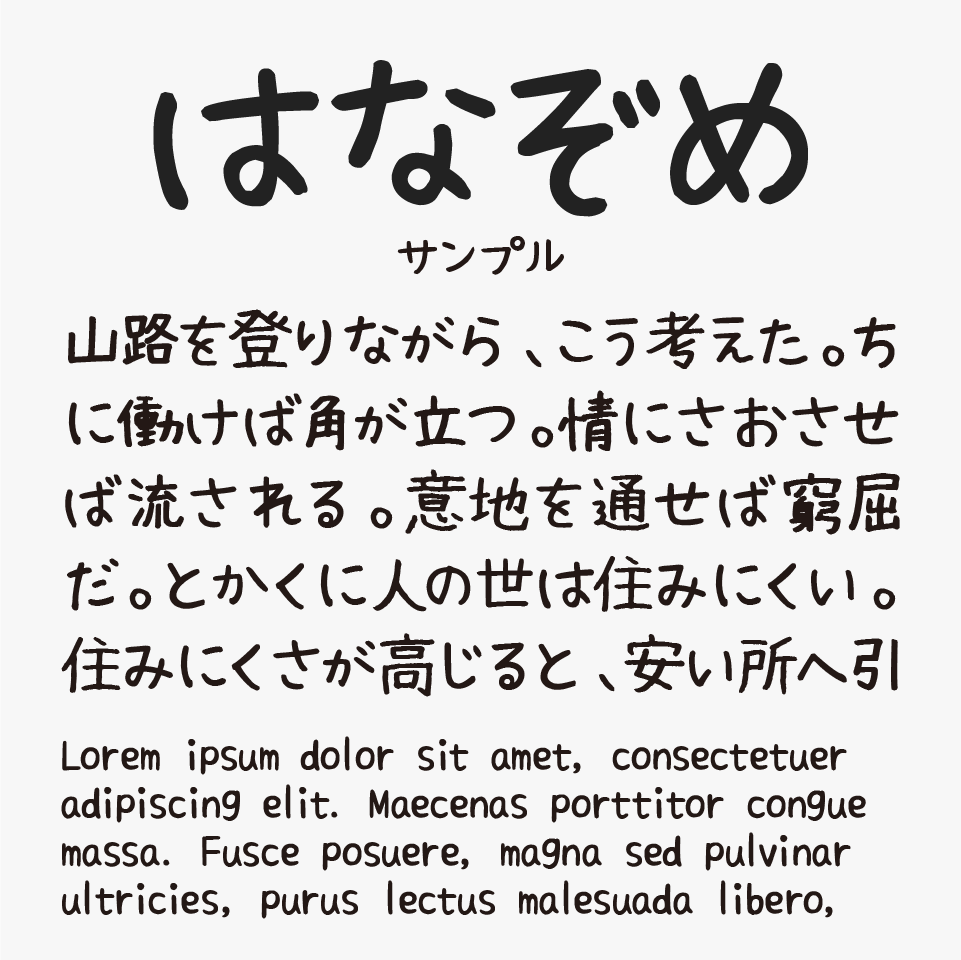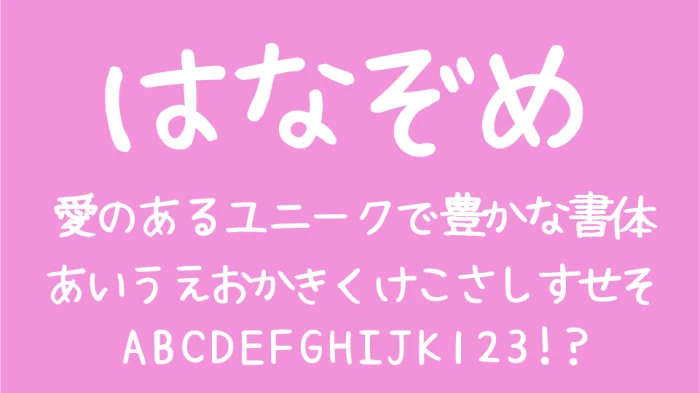
はなぞめフォントは、クセのある崩れたユルい手書き文字の雰囲気がある手書き風フリーフォント。
太めのストロークで構成されていながら重たさは少なく、どこかほっとするような温かみがある手書きフォントです。
文字もサインペンで書いたような太さもあるので、小さく使っても、タイトルに使っても◎
ゆるく書かれているので、子ども向けの教材やイベントチラシに最適です。
収録文字は、ひらがな・カタカナ・教育第二水準までの漢字など6000文字以上が収録されています。